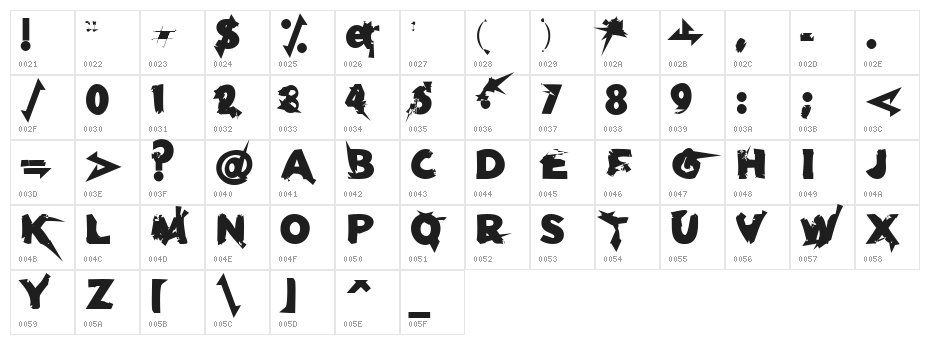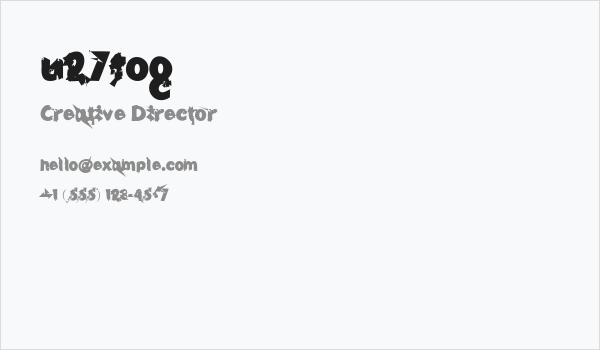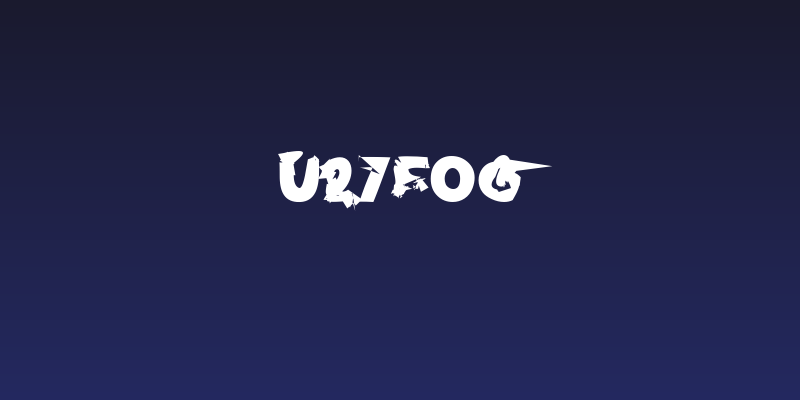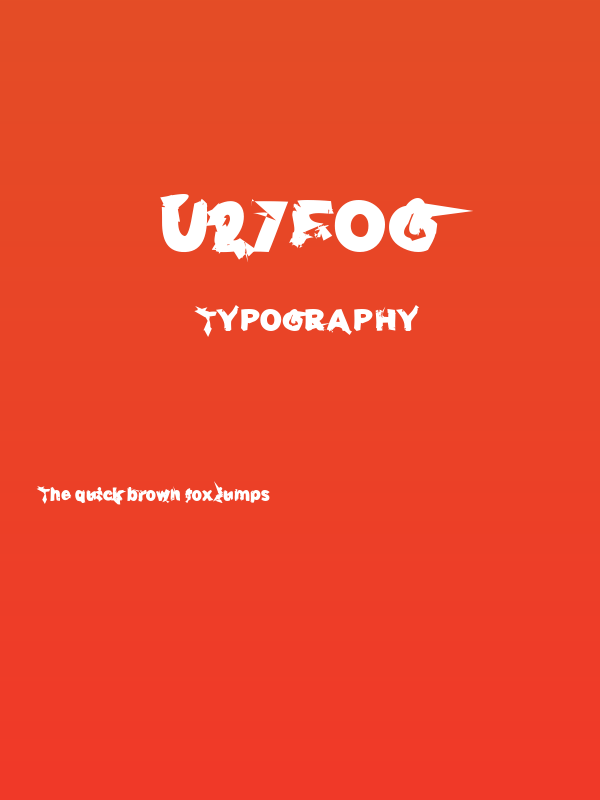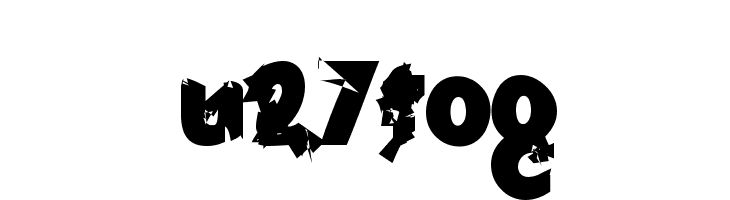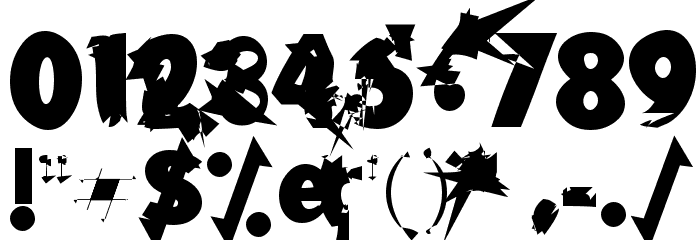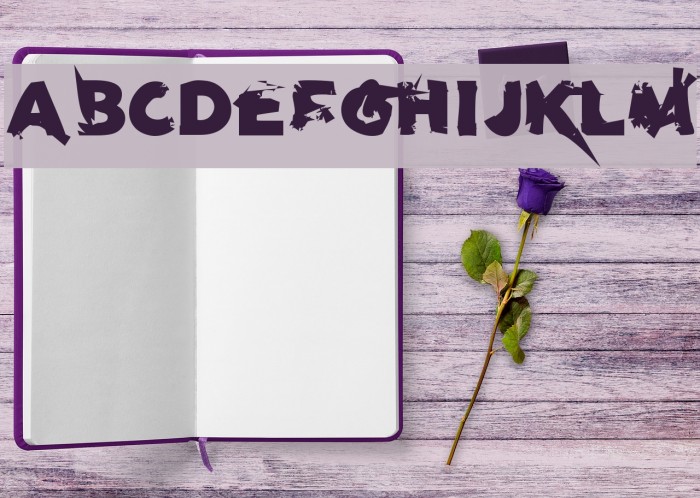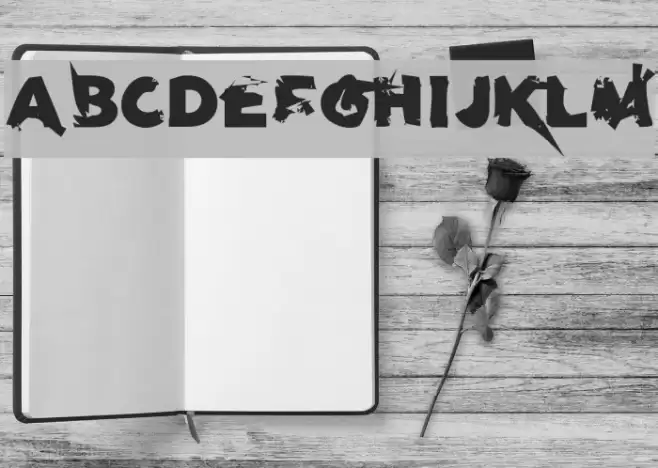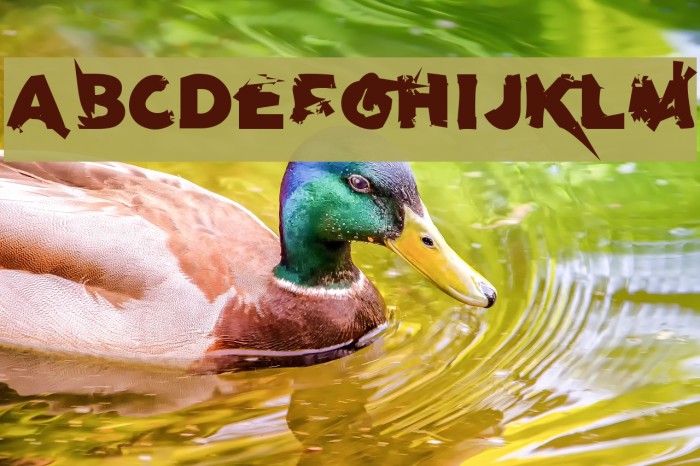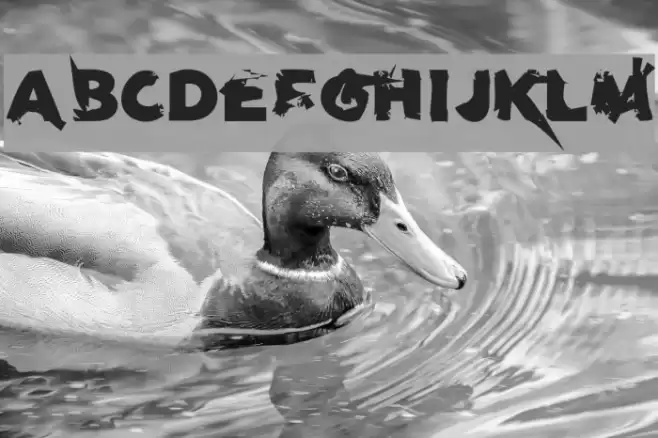
u27fog Font
| Gesamtstil | Modern, Aggressive |
| Anwendungsfall | Headlines, Posters, Logos |
| Vorgeschlagene Projekte | Ideal for music album covers, event posters, or any project requiring a rebellious or energetic aesthetic. |